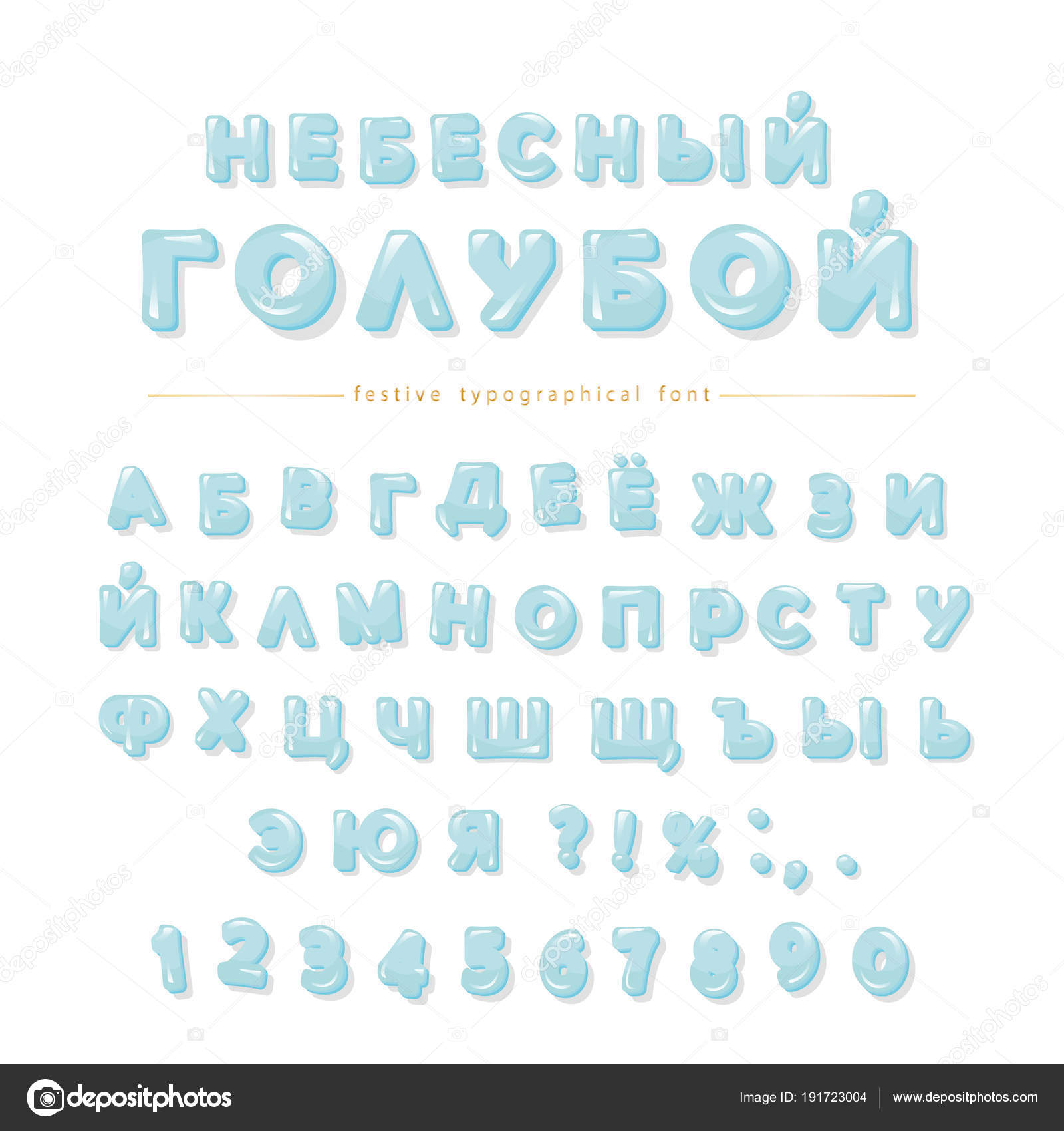
Необычные — Огонь и лед шрифты
48 бесплатных фонов, шрифтов и иконокОжидание праздника Нового года является самым интересным и необычным временем года. Это, пожалуй, даже лучше, чем день рождения. Вся эта предпраздничная суета, витающая в воздухе атмосфера чудес вперемешку с запахом мандарин и хвои, подготовка подарков и новогодних сюрпризов, поздравления и застолья…
Если вы уже начали готовиться к празднику, то хотим вам в этом помочь и представляем вам набор цифровых ресурсов, которые могут вам пригодиться. С их помощью вы сможете красиво оформить поздравительную открытку, новогоднюю почтовую рассылку, свой блог или даже печатное издание. Более 40 бесплатных новогодних шрифтов, картинок, фонов к вашим услугам в Новый год.
Одного взгляда на эти буквы будет достаточно, чтобы понять, какому празднику они посвящены. Снежные шапки, елки, игрушки и подарки представлены здесь в самом широком ассортименте. К сожалению, большинство из них не поддерживают кириллицу.
Kingthings Christmas by Kingthings | Скачать
Ice & Snow Font by AARRGGHH! | Скачать
Christmas Eve by Vanessa Bays | Скачать
DK Father Frost by David Kerkhoff | Скачать
Snowflake Letters by Darrian Lynx | Скачать
Kingthings Flashbang by Kingthings | Скачать
Janda Sparkle and Shine by Kimberly Geswein | Скачать
Bodie MF Holly by Richard William Mueller | Скачать
Christmas/Flakes by Randy Ford
KerstKaarten by Peter Digstra | Скачать
101! Gift by Nght’s Place | Скачать
Ananda Neptouch by Ananda K.
Maharjan | Скачать
PW Christmas by Peax Webdesign | Скачать
Kingthings Willow by Kingthings | Скачать